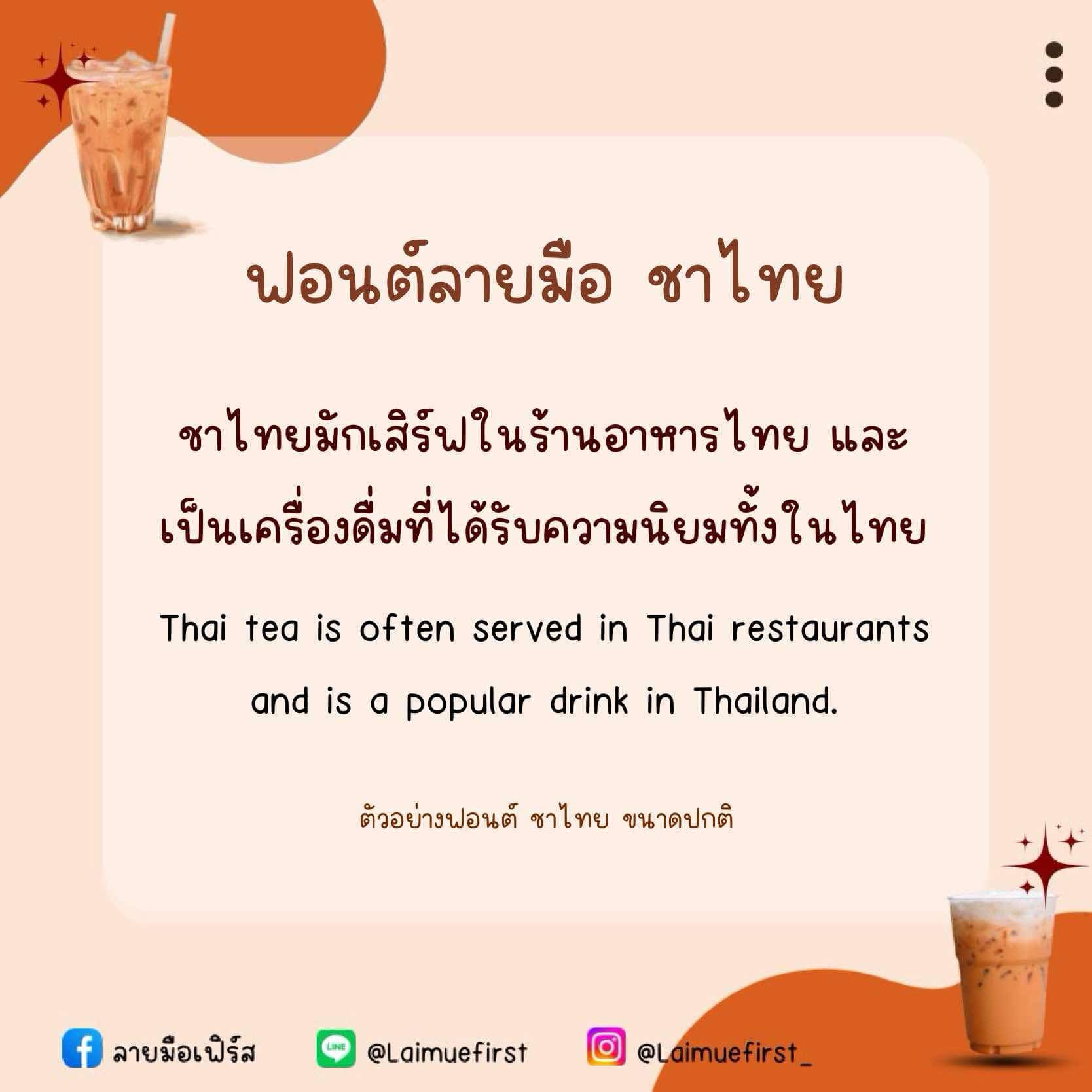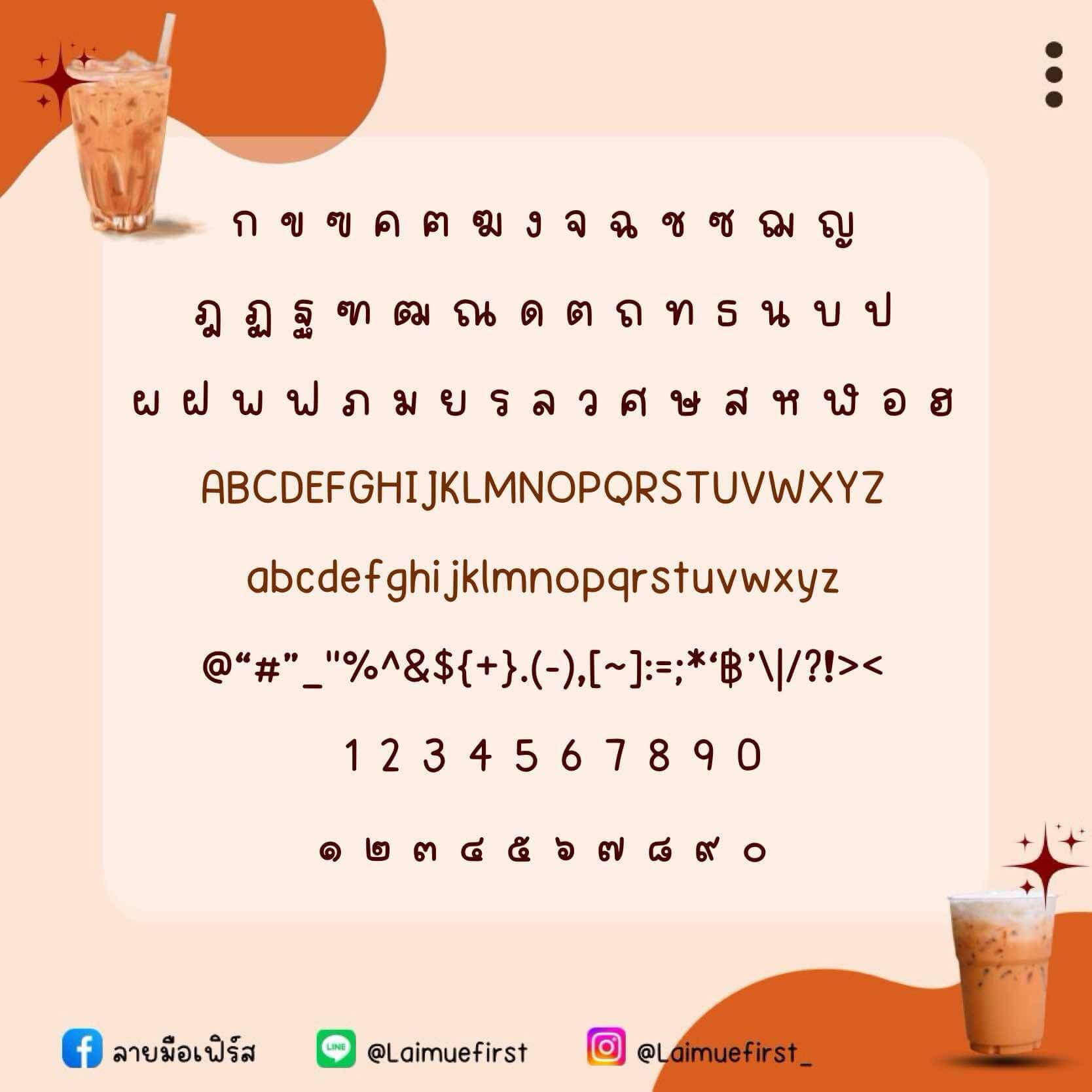
ชาไทย (LMF Chathai)
ฟอนต์ลายมือ ชาไทย (LMF Chathai) แจกฟรี สำหรับทดลองใช้งานแบบส่วนตัว (Demo)
ไฟล์เวอร์ชันทดลองใช้งาน (Demo) ตัวอักษรจะมีขนาดหนา-บางไม่เท่ากัน